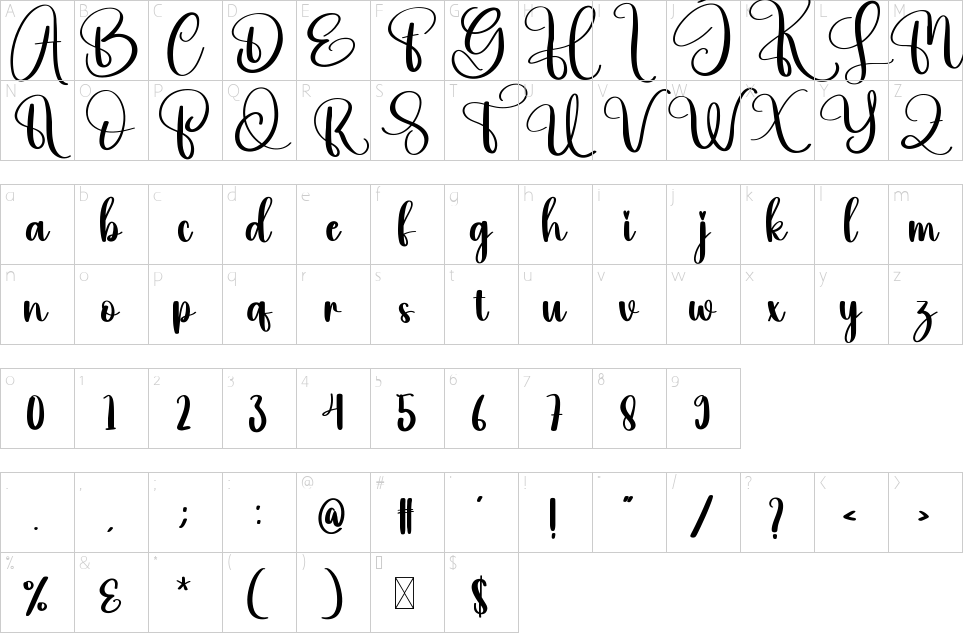
A fonte Alive é uma opção de leitura única e divertida que se tornou um sucesso entre os criativos digitais. Desenvolvida por scratchones, Alive foi projetada para trazer um pouco de vida e entusiasmo à sua interface digital. Suas linhas fluidas e cores vibrantes fazem com que Alive seja tanto uma maneira de personalizar sua experiência de tela quanto uma paixão. Esta fonte já foi descarregada 610 vezes, demonstrando seu valor e popularidade entre designers e criadores de conteúdo. Seja para aplicativos de mensagens, sites pessoais ou até mesmo em designs de apresentação, Alive traz vida e energia a qualquer projeto. Descubra por si mesmo o que Alive pode fazer para enriquecer o seu trabalho digital.